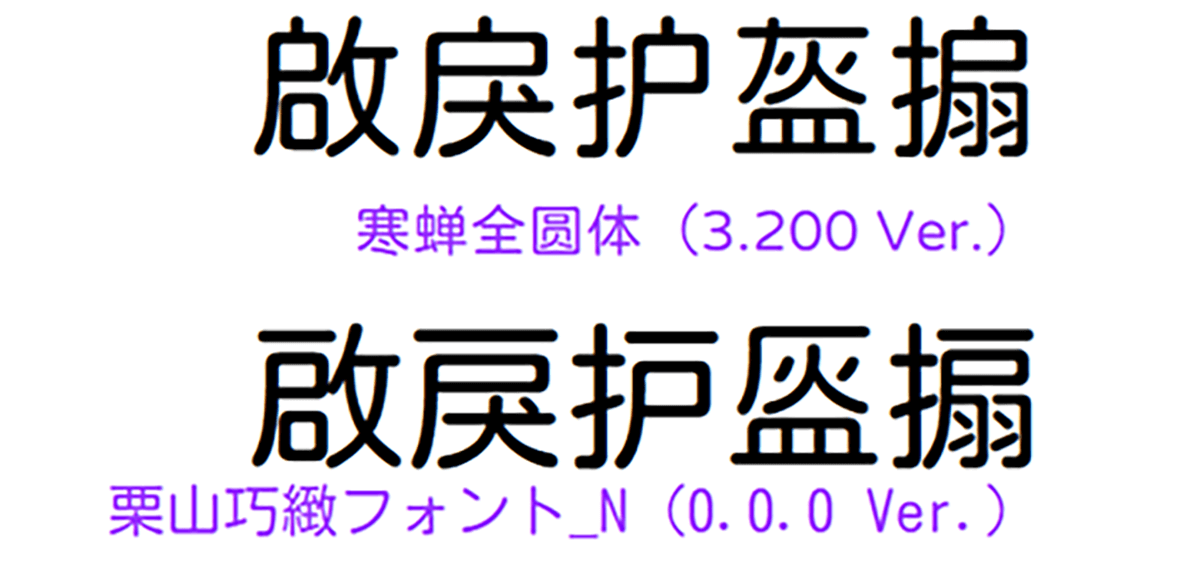
免费圆体:栗山巧緻フォント_N、栗山巧緻フォント_S
栗山巧緻フォント是以Kosugi Maru为基底,进行部分调整后用部份调整过的寒蝉全圆体(ChillRoundF)、部份调整过的昭源环方(Chiron GoRound TC)进行合并的字体。
在尽量保留Kosugi Maru原字图的情况下,用调整过的字体大小粗细尽量接近Kosugi Maru原字图的寒蝉全圆体、昭源环方的字图去进行合并。整个字体与Kosugi Maru原字图风格很接近,且在繁体中文、简体中文、部份生僻汉字的使用上基本不缺字。
与其他改作自Kosugi Maru的字体(寒蝉全圆体、jf open-huninn(粉圆字体))相比,没有动到太多Kosugi Maru原有的字图,所以很多字的风格更贴近Kosugi Maru。
在尽量保留Kosugi Maru原字图的情况下,用调整过的字体大小粗细尽量接近Kosugi Maru原字图的寒蝉全圆体、昭源环方的字图去进行合并。整个字体与Kosugi Maru原字图风格很接近,且在繁体中文、简体中文、部份生僻汉字的使用上基本不缺字。
与其他改作自Kosugi Maru的字体(寒蝉全圆体、jf open-huninn(粉圆字体))相比,没有动到太多Kosugi Maru原有的字图,所以很多字的风格更贴近Kosugi Maru。
从Kosugi Maru到KURIYAMAKOUCHIFONT,做了怎样的改作?
第001步・对Kosugi Maru做调整
把Kosugi Maru之中可能搞混(编码不同且字形有点不同但字图完全一样所以可能搞混)的字图「昻」给删除。
第002-1步・对寒蝉全圆体(ChillRoundF)做调整
把寒蝉全圆体之中可能搞混、搞错的字图给删除(譬如说,愦、嘒、丢、匀……等字)。
根据自己的喜好,把寒蝉全圆体之中的某些字图与其对应的「OpenType特性的字形异体字图」给互换,尽量用更接近日本新字体、旧字体的部件字形的字图来显示文字(譬如说,启、戾、护、扇……等字)。
把寒蝉全圆体中的所有字图给放大、增加字宽……,让其尽量贴近Kosugi Maru的字图风格。
第002-2步・把调整过的Kosugi Maru与调整过的寒蝉全圆体的字图进行合并
用调整过的寒蝉全圆体的字图补充到调整过的Kosugi Maru。对调整过的Kosugi Maru之中缺少的字图进行补字。
第003-1步・对昭源环方(Chiron GoRound TC)做调整
把昭源环方中的所有字图给放大、增加字宽……,让其尽量贴近Kosugi Maru的字图风格。
第003-2步・把「调整过的Kosugi Maru与调整过的寒蝉全圆体的字图进行合并之后的『成果』」与调整过的昭源环方的字图进行合并
用调整过的昭源环方的字图补充到之前得到的「成果(调整过的Kosugi Maru与调整过的寒蝉全圆体的字图进行合并之后得到的)」。对其之中缺少的字图进行补字。
其中,N(Normal)版本是正常显示各种汉字的普通版本。 S(Special)版本是尽量以日本常见写法的字图来强制显示很多繁体字和简体字的特别版本(譬如说,用『亜』的字图来显示『亚』、『亚』)。
(备注:在S版本之中,对于某些汉字来说,如果可能会搞混的话则不会用日本常见写法的字图来强制显示繁体字和简体字。譬如说,发……等字)